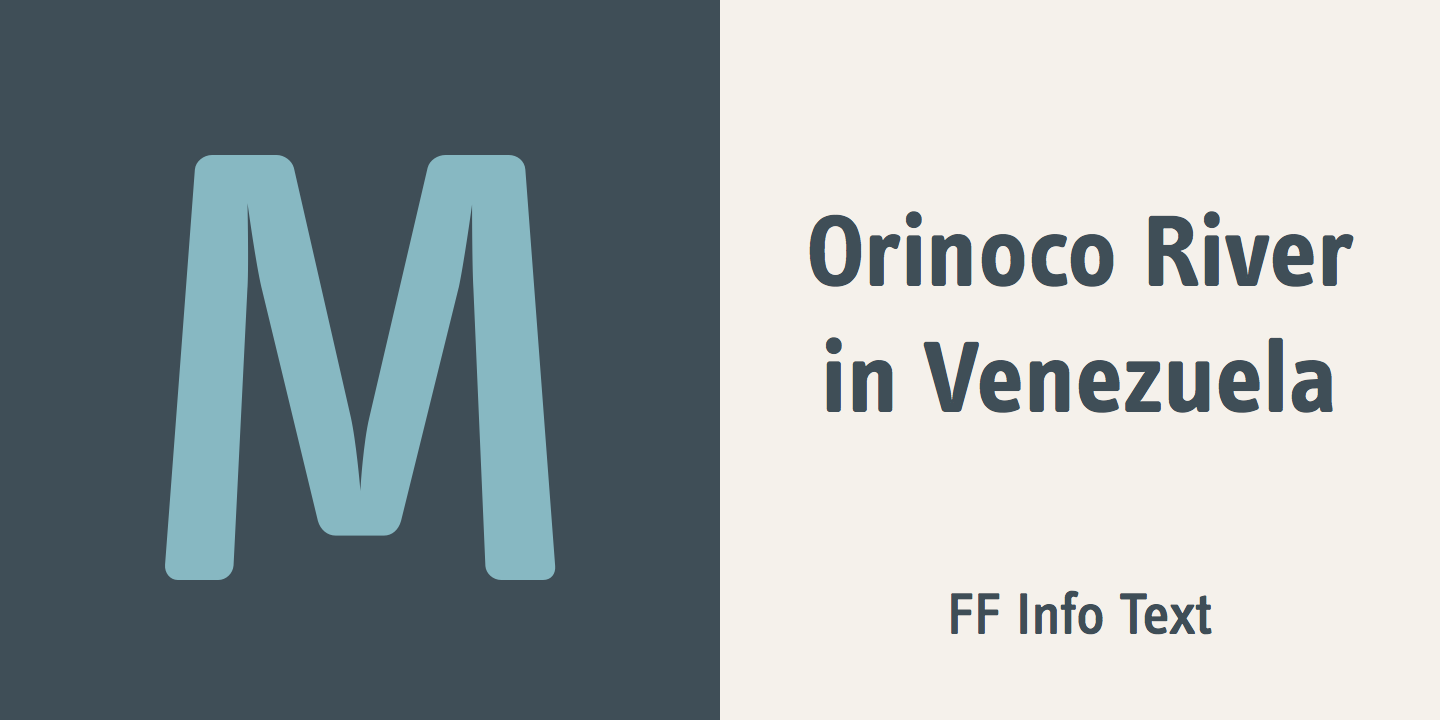
Nach einem schweren Brand am Düsseldorfer Flughafen entwickelt MetaDesign ein neues Leitsystem. Die dabei eingesetzte Schrift basiert auf einem Entwurf von 1988, den Erik Spiekermann für die italienische Pharma-Firma Fidia schuf.
Die FF Info besticht durch ihre klare Formensprache und gute Leserlichkeit. Kritische Buchstabenpaare sind möglichst unmissverständlich gestaltet.